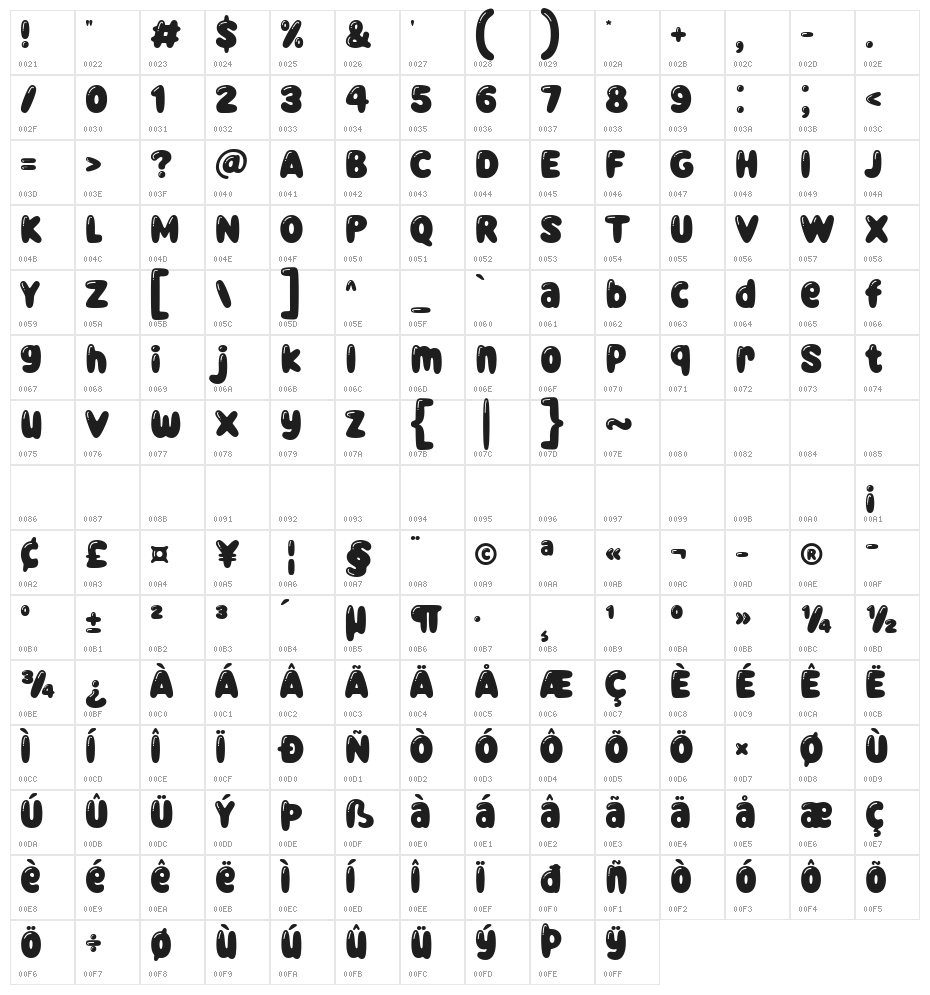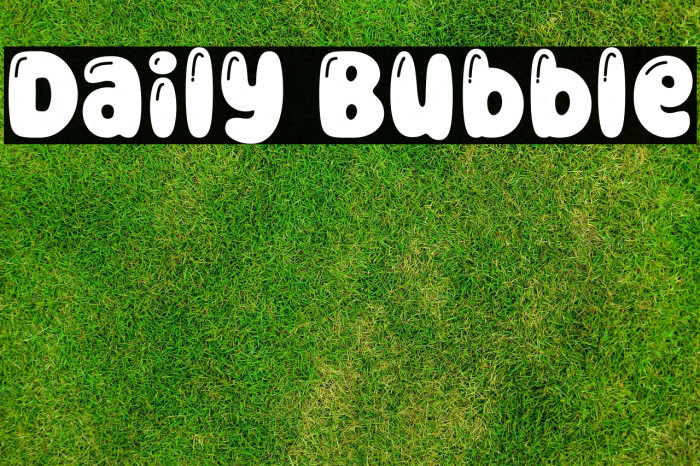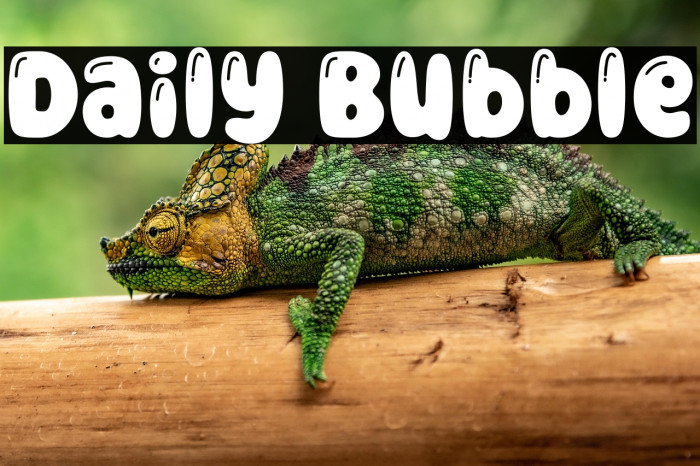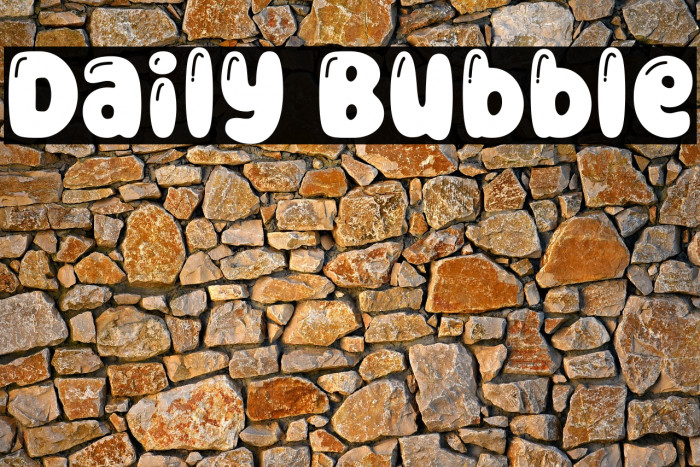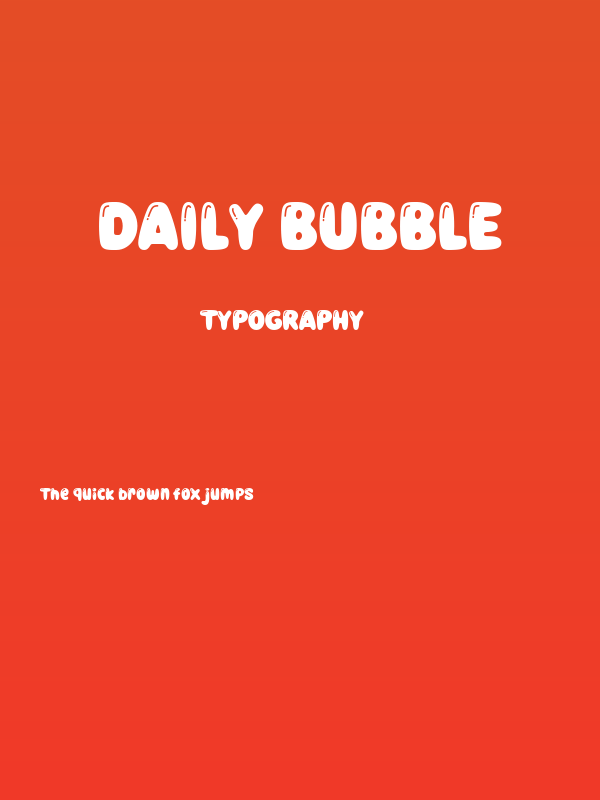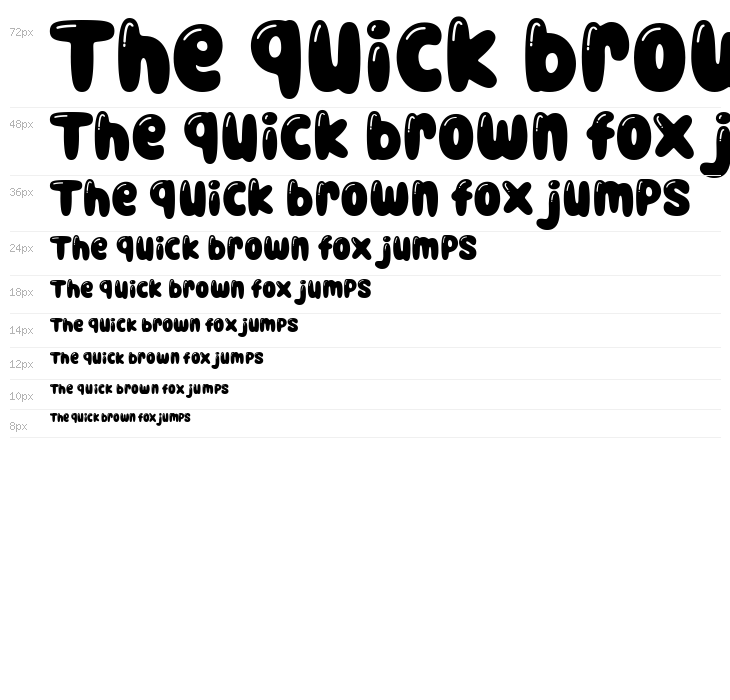
Daily Bubble Font
| Gesamtstil | Playful, Whimsical |
| Vorgeschlagene Projekte | Ideal for children's books, playful branding, party invitations, and creative posters. |